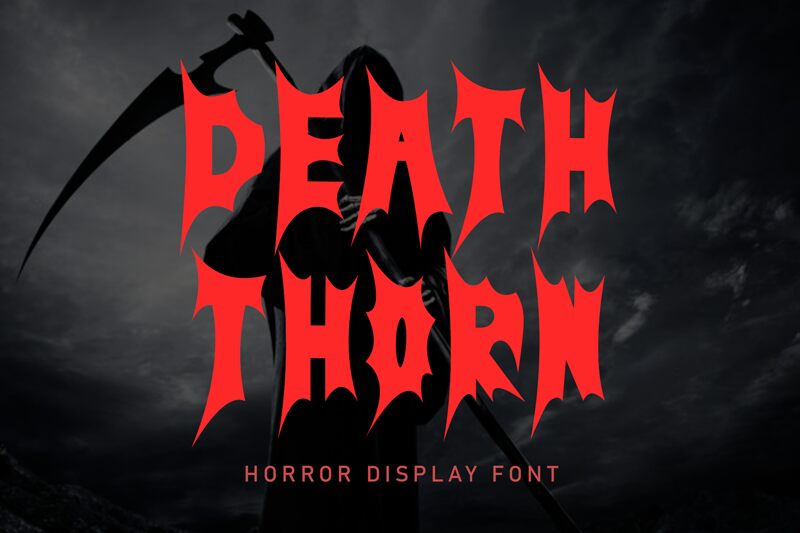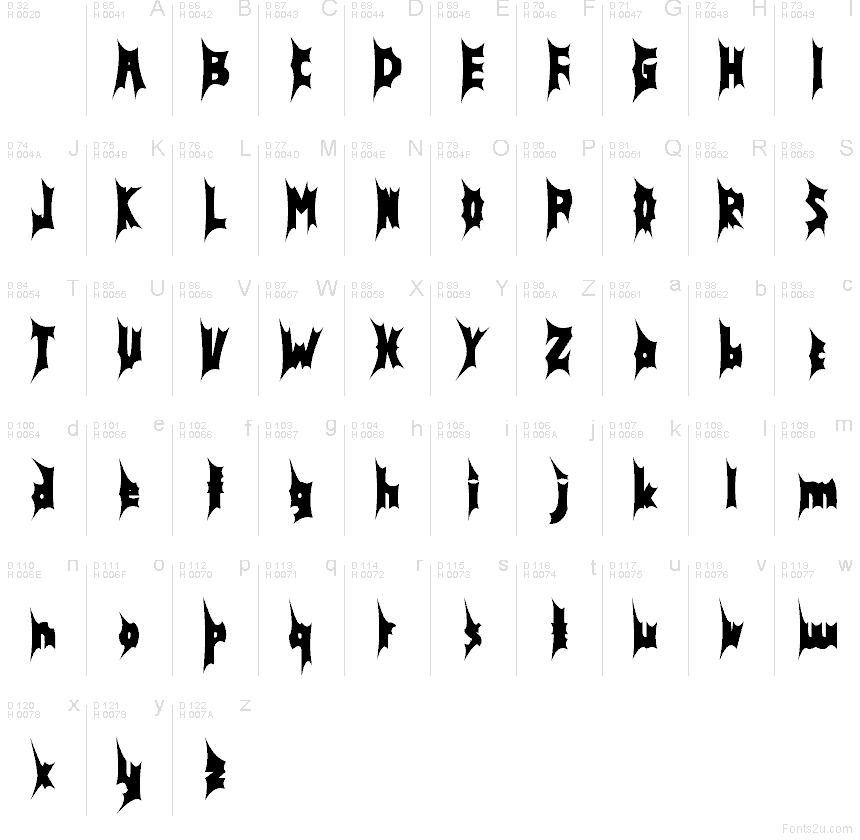
Death Thorn
Death Thorn de Yoga Letter es una tipografía gótica gratuita con trazos afilados y bordes puntiagudos que confieren a las letras un ritmo anguloso y cortante. Sus formas parecen talladas y espinadas, con aperturas estrechas y acabados secos y precisos que mantienen el diseño tenso y ornamental.
Death Thorn funciona a la perfección en pósteres de terror, arte para bandas de metal, títulos de videojuegos, tatuajes y diseños para eventos oscuros, ya que su construcción dentada transmite la misma energía espinosa en cada glifo. Death Thorn también es ideal para logotipos, portadas y titulares decorativos cuando buscas formas de letra que se sientan más como un emblema afilado que como un texto convencional.